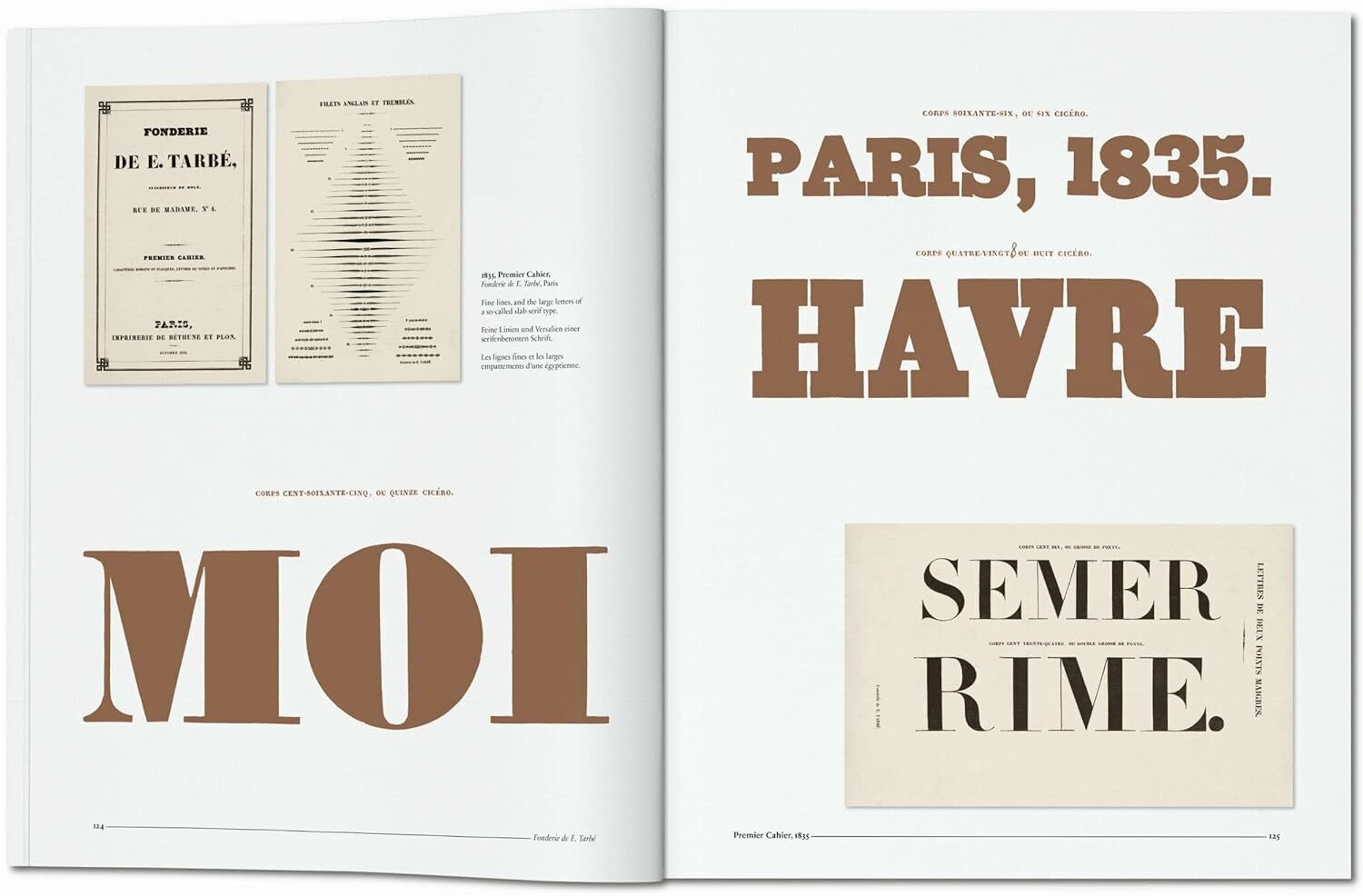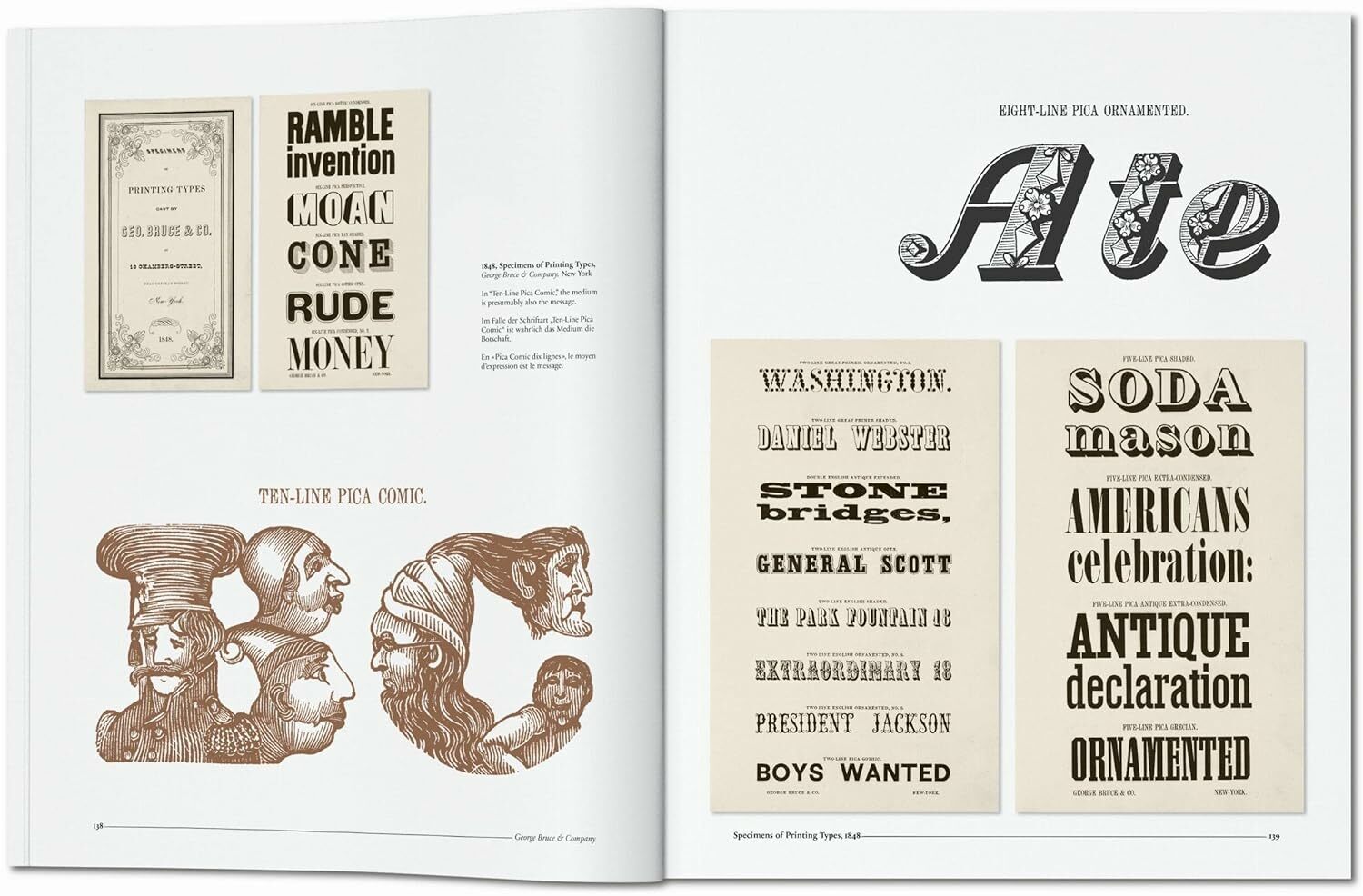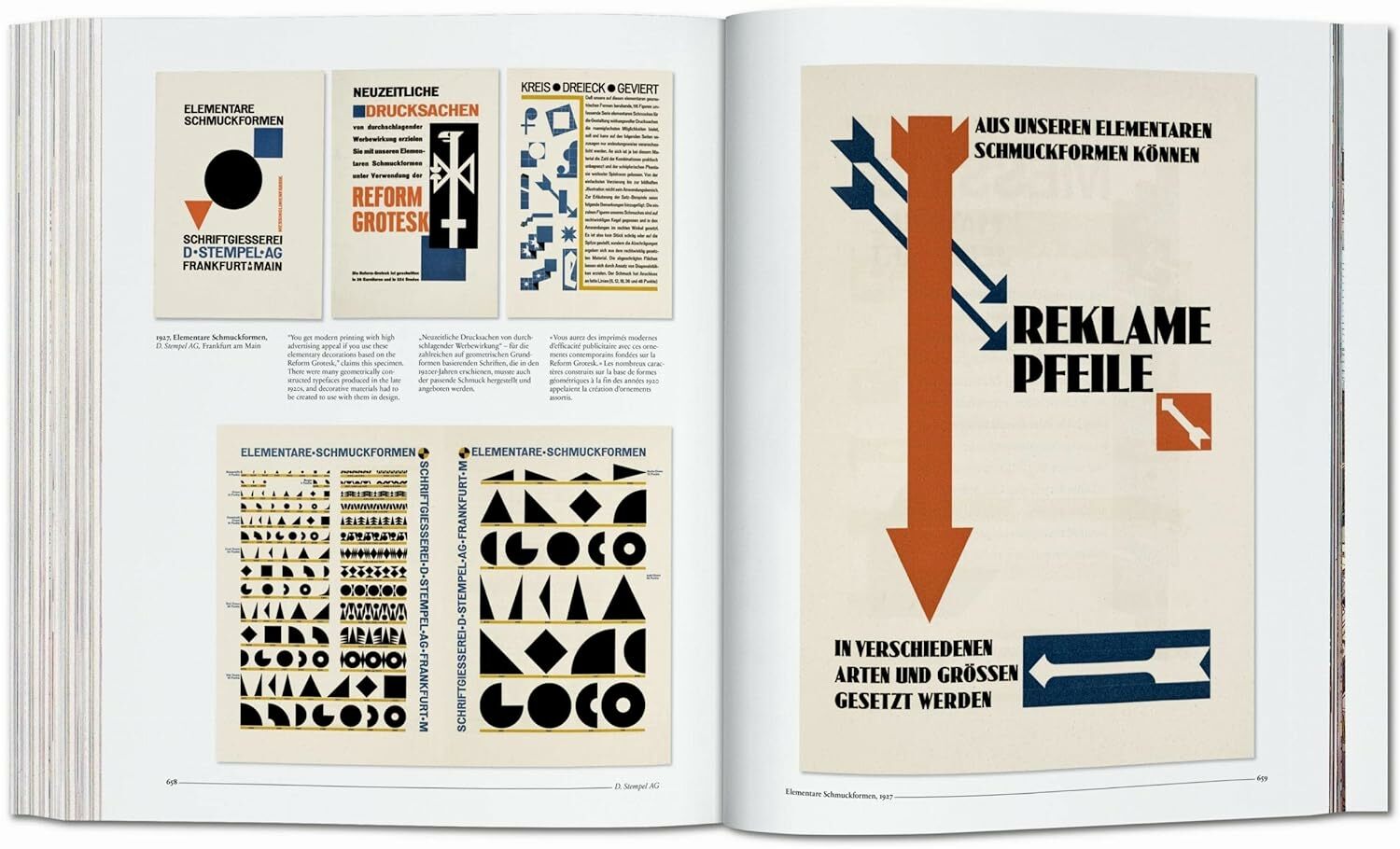
Type. A Visual History of Typefaces & Graphic Styles
【書籍簡介】
這本全面的收藏集提供了從1628年到20世紀中葉字體設計的詳盡概覽。這些精美設計的目錄來自一個著名的荷蘭收藏系列,展示了印刷字母的演變過程,涵蓋了羅馬體、斜體、粗體、半粗體、窄體及寬體字型標本。書中還包括邊框、裝飾圖案、首字母以及其他裝飾,並附有石版印刷的範例,以及由招牌畫家、碑銘雕刻家和書法家創作的字母作品。
書籍的第一部分涵蓋了20世紀前的字體,由編輯 Cees de Jong 和收藏家 Jan Tholenaar 撰寫的文章組成。第二部分探討了從1900年到20世紀中葉的字體發展,並包含 Alston W. Purvis 撰寫的歷史概述。書中展示的字體設計師包括:威廉·卡斯隆(William Caslon)、弗里茨·赫爾穆特·艾姆克(Fritz Helmuth Ehmcke)、彼得·貝倫斯(Peter Behrens)、魯道夫·科赫(Rudolf Koch)、埃里克·吉爾(Eric Gill)、揚·凡·克里姆彭(Jan van Krimpen)、保羅·雷納(Paul Renner)、揚·齊赫爾德(Jan Tschichold)、A. M. 卡桑德(A. M. Cassandre)、阿爾多·諾瓦雷塞(Aldo Novarese)和阿德里安·弗魯提格(Adrian Frutiger)。